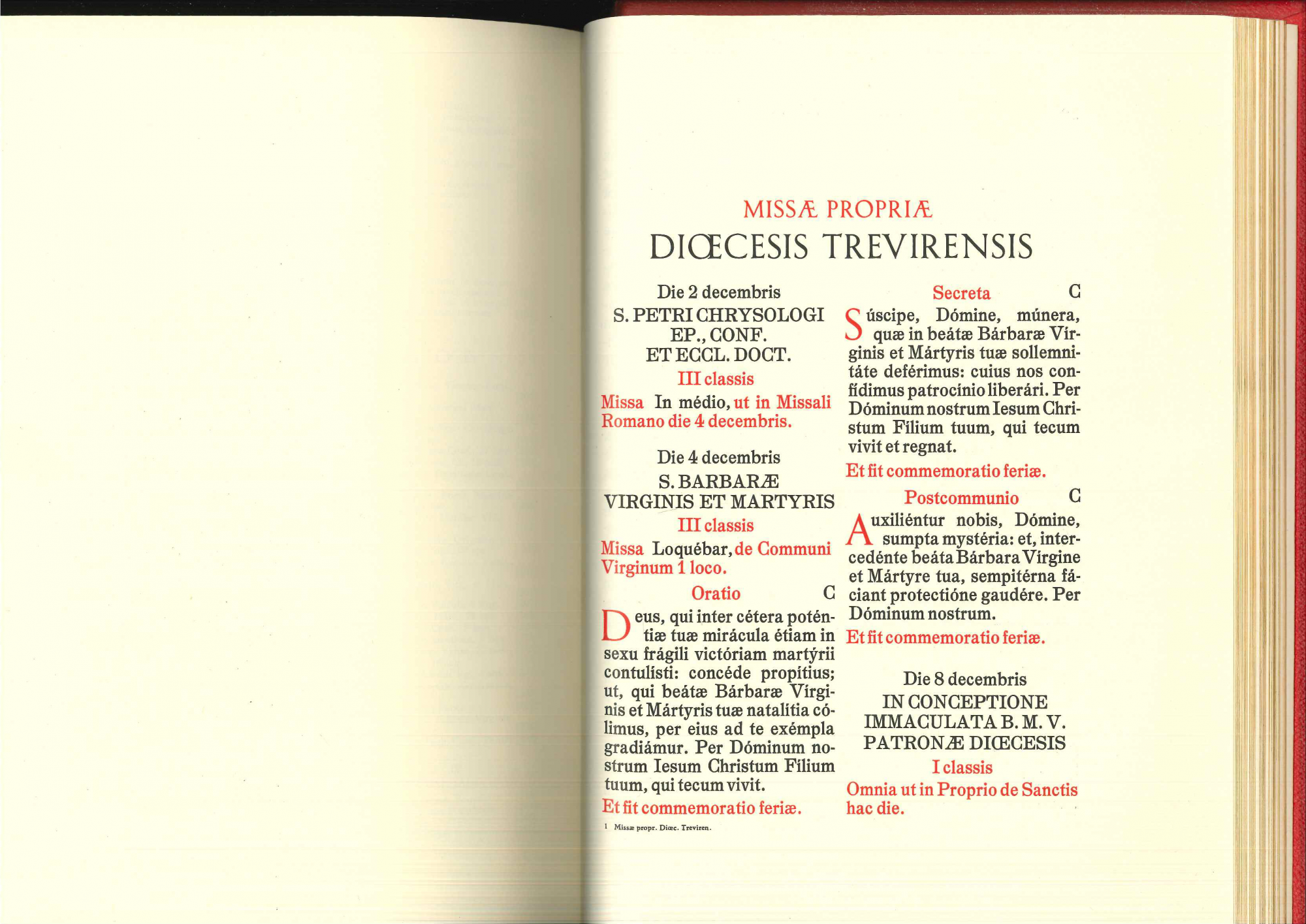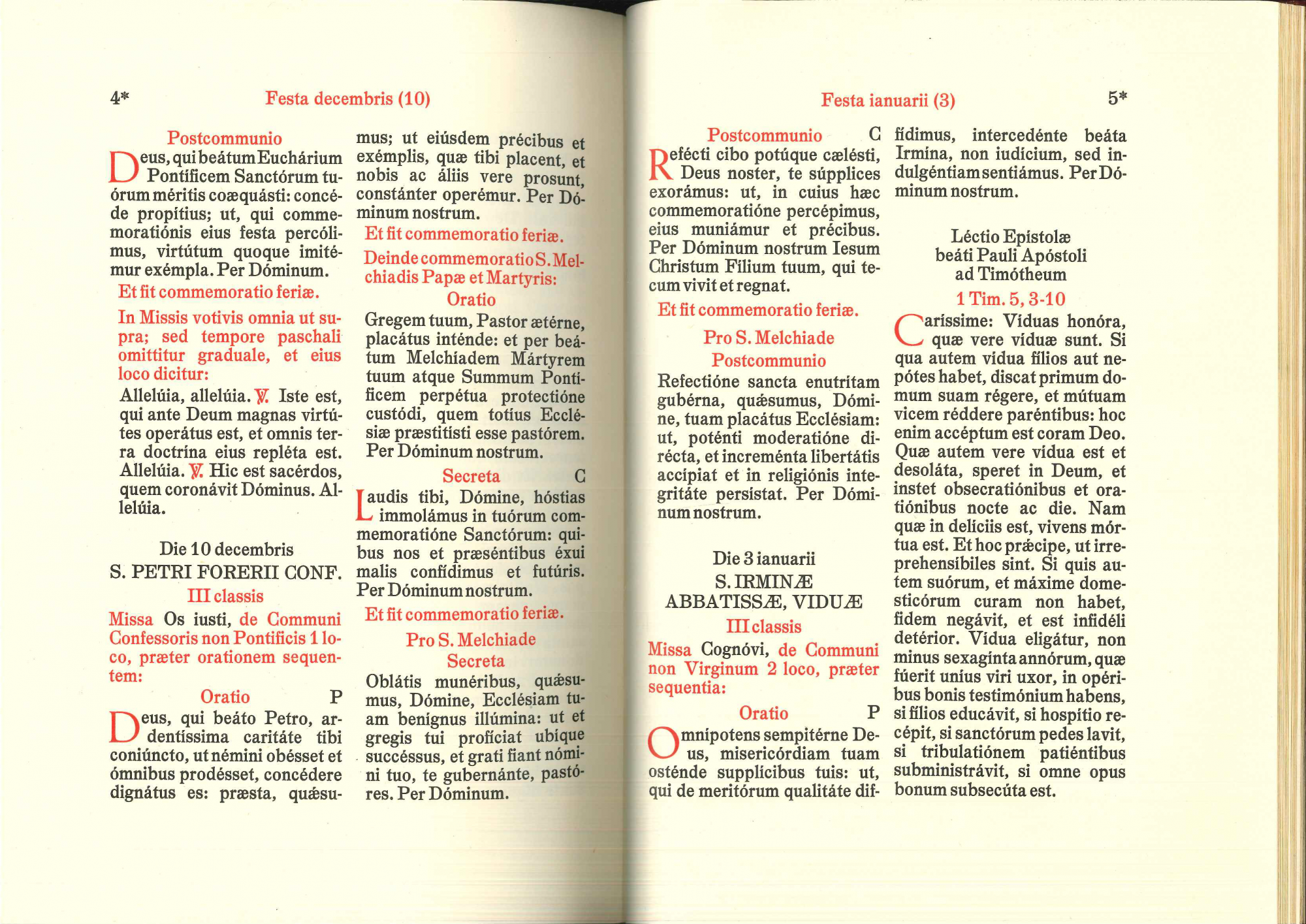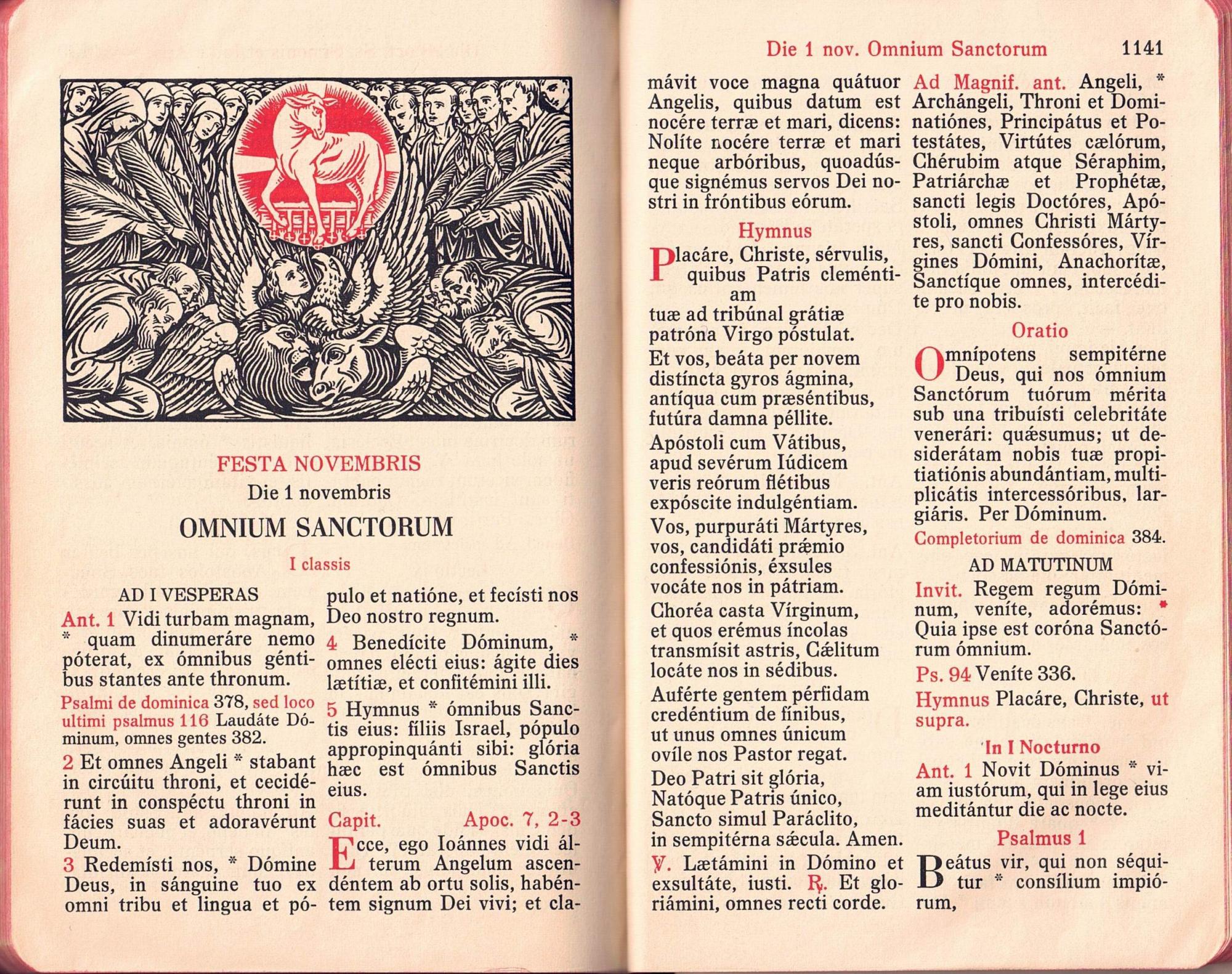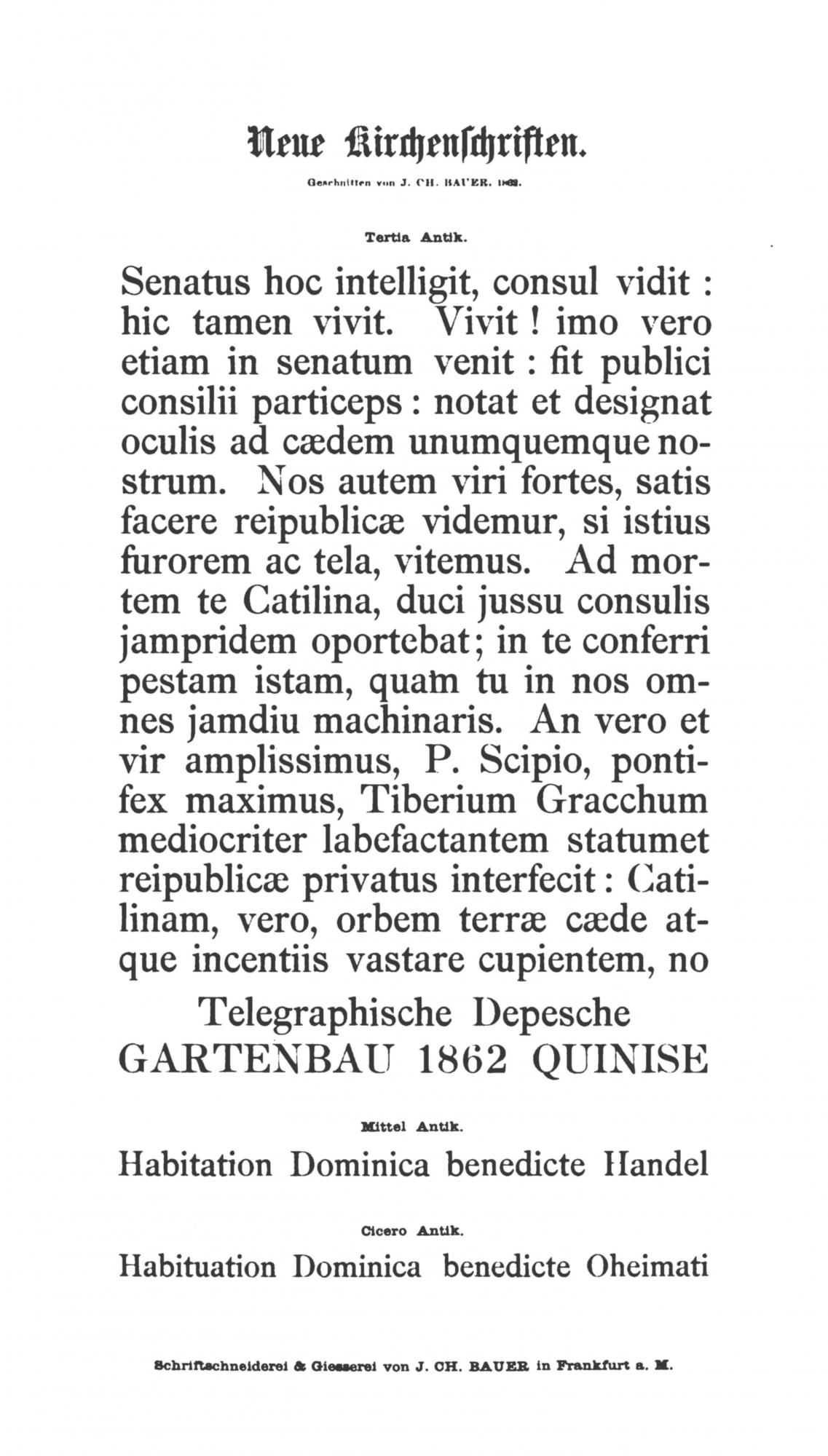
Suche Schriftart aus katholischem Missale
Suche eine Schriftart, die bis in die 60er Jahre in katholischen liturgischen Büchern in lateinischer Sprache aus dem Friedrich Pustet Verlag in Regensburg häufig bzw. fast ausschließlich verwendet wurde, möglichst in digitaler Form. Die Auszeichnungsschriften im Beispiel sind die Genzsch-Antiqua von Friedrich Bauer (Genzsch & Heyse) sowie die Weiß-Antiqua von Friedrich Rudolf Weiß (Bauersche Gießerei) -- aber der Rest? Man beachte besonders das kleine f, den Fuß des R und das Vorhandensein von œ- und æ-Ligatur mit Gravis sowie eines gestrichenen V und R.
Hallo @Horst Worst, ich bin damit leider noch nicht weitergekommen. Fände es aber auch sehr interessant, diese Schrift zu erfahren – wenn also einer der Kollegen hier trumpfen kann: nur zu …
Das Wenige, was ich noch recherchieren konnte: Bei Luc Devroye und auch andernorts findet man die Angabe, dass Friedrich Pustet eine "Neue Kirchenschrift" aus der Bauerschen Gießerei exklusiv nutzte, die J. Chr. Bauer um 1890 (so Devroye, nach anderen 1850-1861) geschnitten hatte. Allerdings soll es sich dabei um eine Renaissance-Antiqua gehandelt haben. Kann das jemand bestätigen? Leider stehen mir keine Schriftmuster zur Verfügung.
Ansonsten ist die gesuchte Schrift eine ausgesprochene Spezialschrift, die möglicherweise ausschließlich von Fr. Pustet genutzt wurde. Dafür spricht, dass die Schrift auf den Satz lateinischer liturgischer Texte zum Gebrauch bei schlechten Lichtverhältnissen optimiert ist (entspr. Sonderzeichen, die sehr klotzigen Akzente); außerdem war Pustet seinerzeit einer von nur drei Verlagen weltweit, die amtliche Texte der katholischen Kirche drucken durften (die anderen waren Desclée et Cie. in Tournai und die Typographia [Polyglotta] Vaticana in Rom). Andere hatten dafür also keine Verwendung. (Desclée, berühmt für den Druck von Quadratnotation, benutzte zuletzt m.W. eine Goudy, die Typographia Vaticana eine Romana, die dort "Elzeviriana" genannt wurde, und später eine Garamond.) Gut möglich also, dass dazu überhaupt nichts Schriftliches existiert.
Ich habe nun aus der Not heraus begonnen, die Schrift selbst zu digitalisieren. Mein Erstlingswerk in dieser Richtung -- mal sehen, ob's was wird...
PS: Einen Fehler in meinem ersten Post muss ich noch korrigieren: Die Auszeichnungsschrift ist natürlich überall die Weiß-Antiqua; die Genzsch-Antiqua verwendet Pustet zwar meist zusätzlich, aber nicht in diesem Beispiel.
So, nun habe ich die Digitalisierung soweit in Angriff genommen; stellvertretend für die Lesegrößen habe ich mich an der Borgis-Garnitur vergangen, denn da hatte ich als Vorlage ein Brevier mit vorzüglichem Druckbild zur Verfügung. Das Ergebnis ist sicher noch nicht perfekt, aber ich lerne ja noch und hoffe auf viele Tips von den alten Hasen hier, mit denen ich das bisher Geschaffte noch verbessern und dann vielleicht auch noch einen Schaugrad bewältigen kann. Besonderer Dank geht schon mal unbekannterweise an @catfonts (wie zitiert man User?), dessen zahlreiche über das Forum verteilte Erfahrungsfrüchte ich mit Eifer gelesen und nach Kräften genutzt habe.
Als Muster und zum Testen, ob die Anmutung des Originals rüberkommt, habe ich mal eine Brevierdoppelseite nachgesetzt und unten angehängt; hier das Original (Wie verkleinert man Bilder?):
Eigentlich wollte ich das Baby "Ratisbona" nennen, habe aber dann doch noch herausgefunden, dass es sich tatsächlich um die schon vermuteten, aber als Vermutung wieder verworfenen "Neuen Kirchenschriften" von Chr. Fr. Bauer aus dem Jahr 1862 handelt -- die Schrift roch für mich einfach überhaupt nicht nach Renaissance-Antiqua, das hatte mich kirre gemacht, aber es ist natürlich eine solche, auch wenn man ihr ihre Entstehungszeit doch stark anmerkt, wie ich finde.